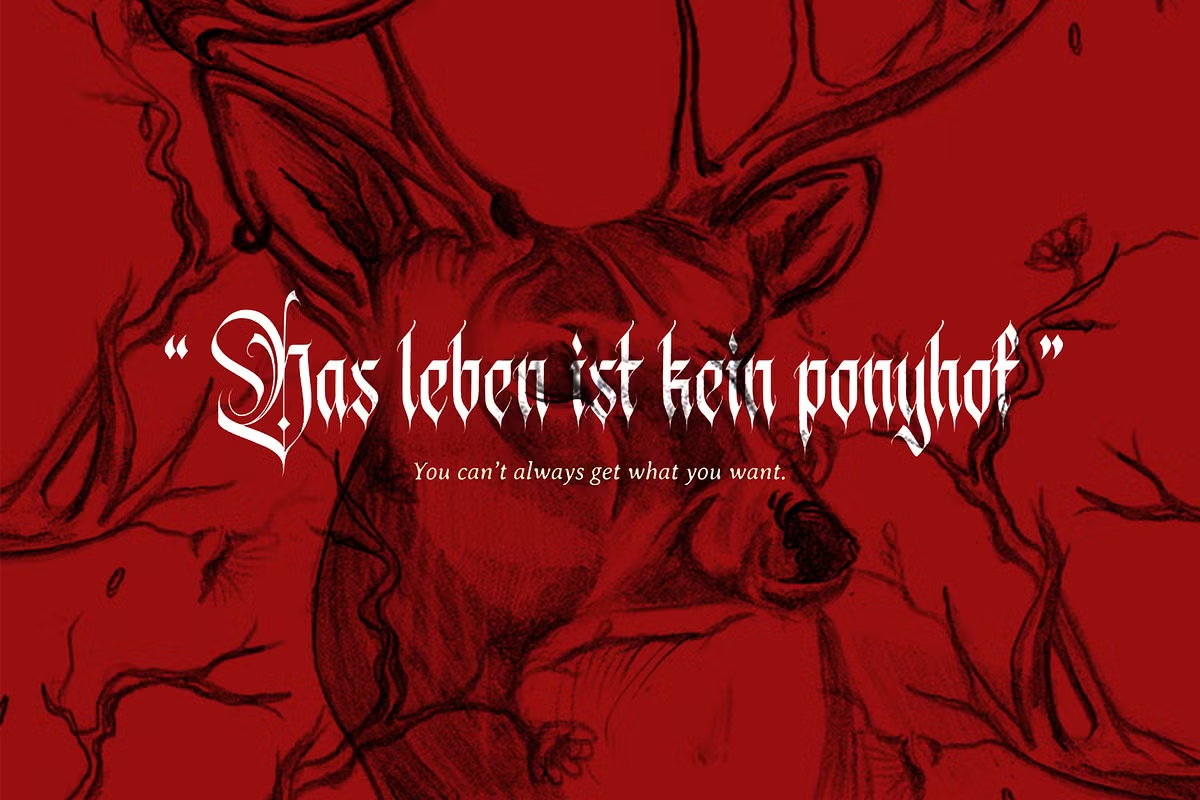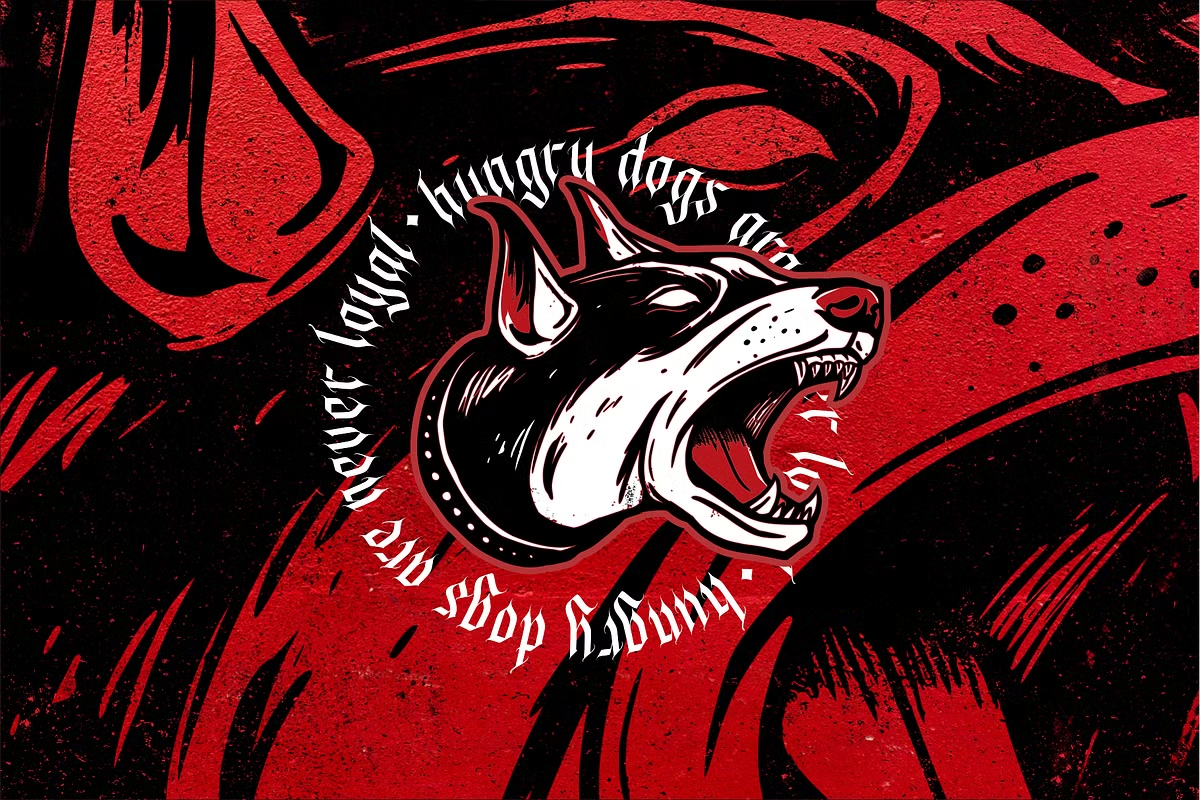
Aviorte Font
Description de Aviorte Font
Aviorte est une police de lettres noires élégante, propre, formelle et magnifique. La majuscule avec un élément ornemental le rend très beau et décoratif. Il convient aux titres, aux conceptions de logos, aux conceptions de badges, à la marque de conception de t-shirts, etc.